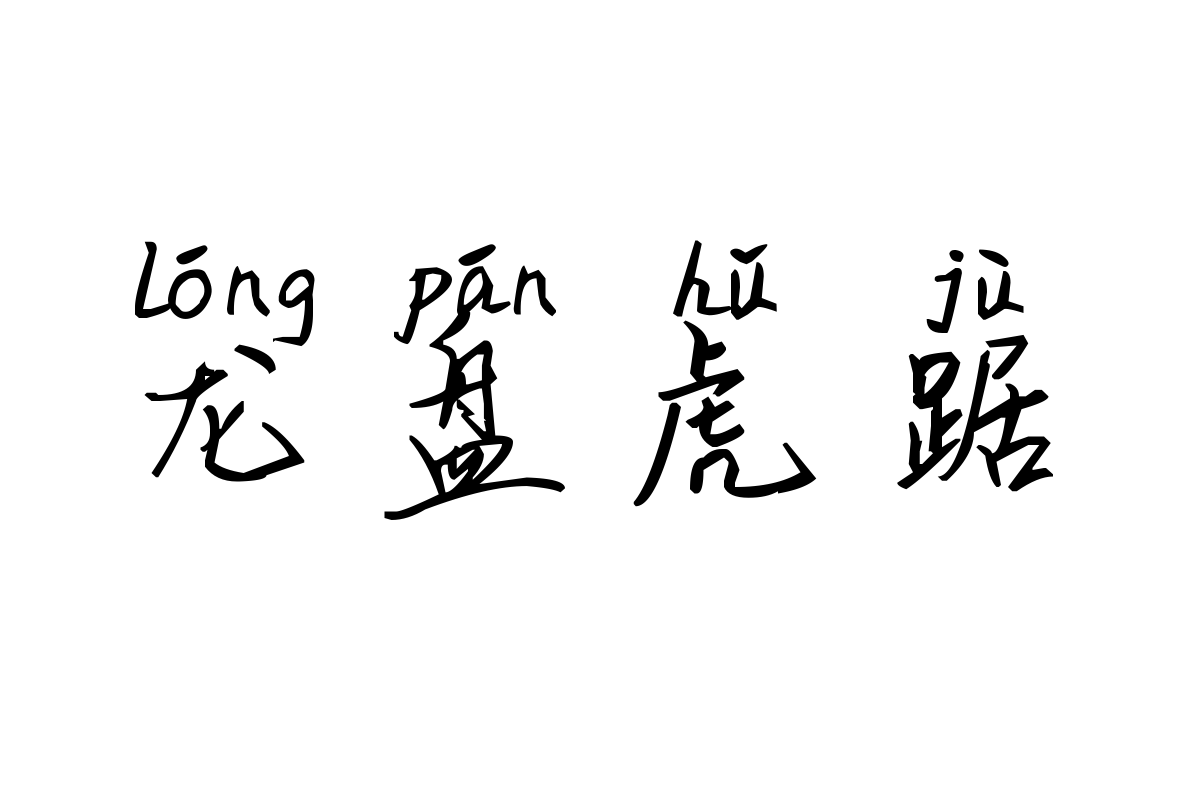
米开倾城时光拼音体是一款具有独特设计感的字体,它采用了现代简约的风格,线条流畅,字形清晰。这款字体适合用于各种需要展示文字信息的场合,如网站、海报、广告等。它的笔画粗细适中,既有力量感又不失优雅,给人一种舒适的感觉。此外,米开倾城时光拼音体还具有一定的艺术性,可以作为设计师们表达创意和个性的工具。总的来说,这款字体是一款非常实用且美观的字体选择。